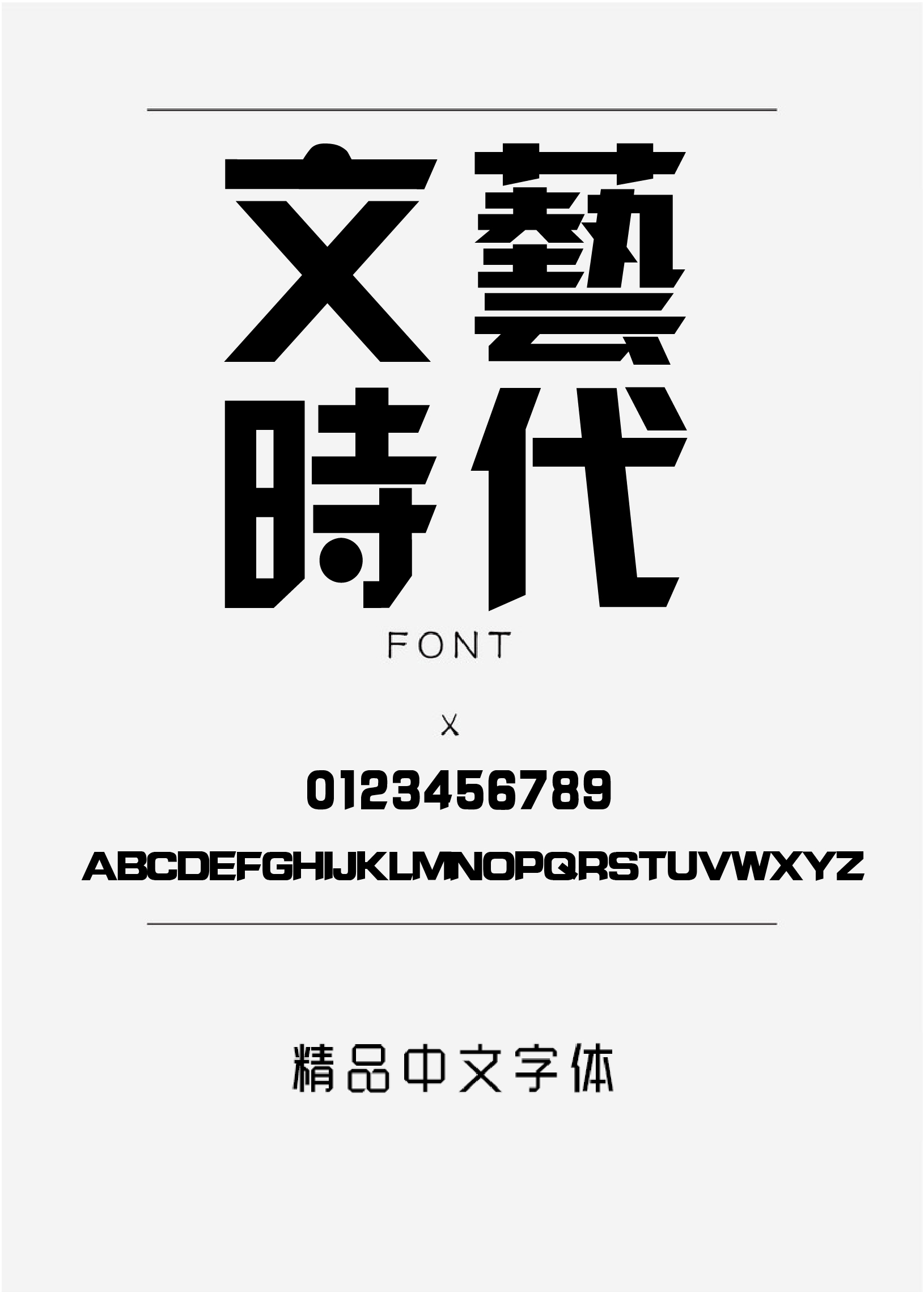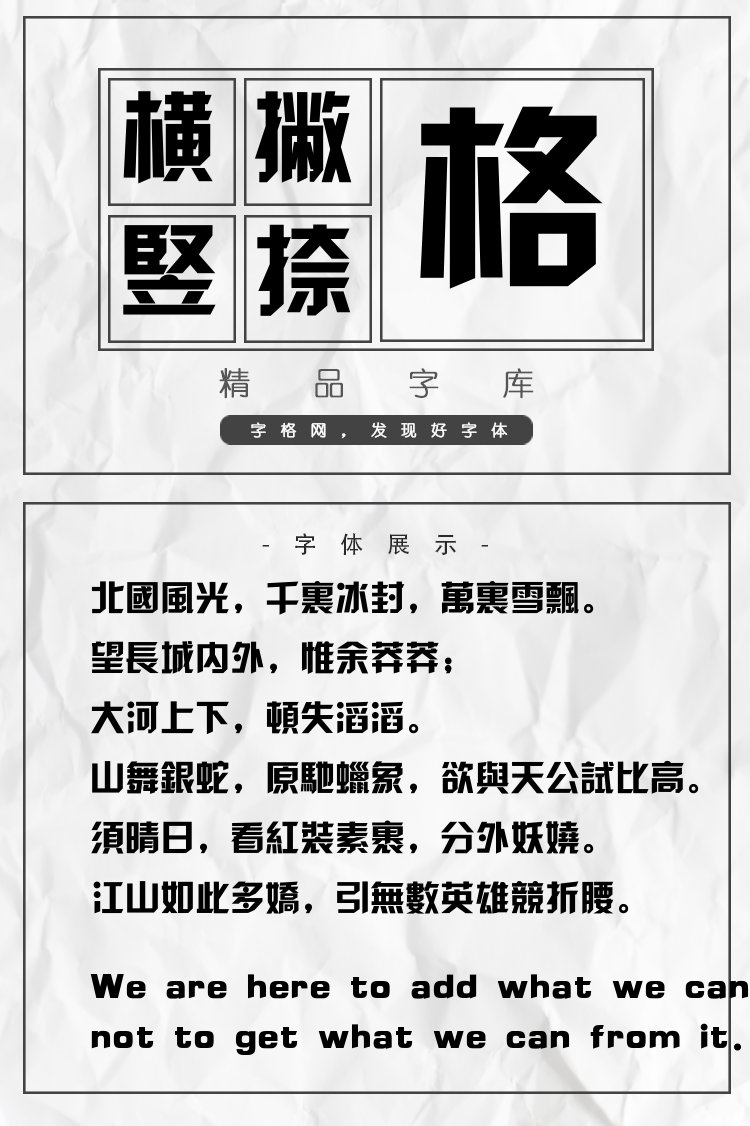
汉仪菱心体繁
字体说明:汉仪菱心体繁字体是一款可商用的毛笔书法,英文手写,手写体字体,该字体包含6763个中文、字母、符号和数字,具有充满力量、大气、豪放、稳重、手写风、古典 的风格,可以满足您设计上的各种需求,该字体主要用于电商、广告、视频影视、海报企宣、书籍 等场景, 您不但可以在字格网下载汉仪菱心体繁,同时还有众多毛笔书法字体、创意字体等可供选择!